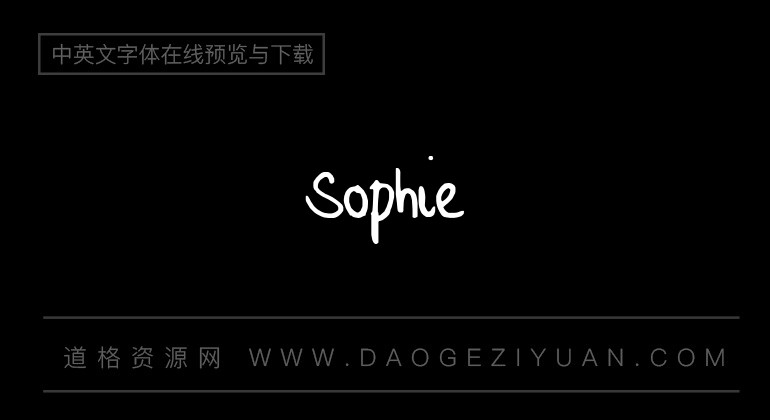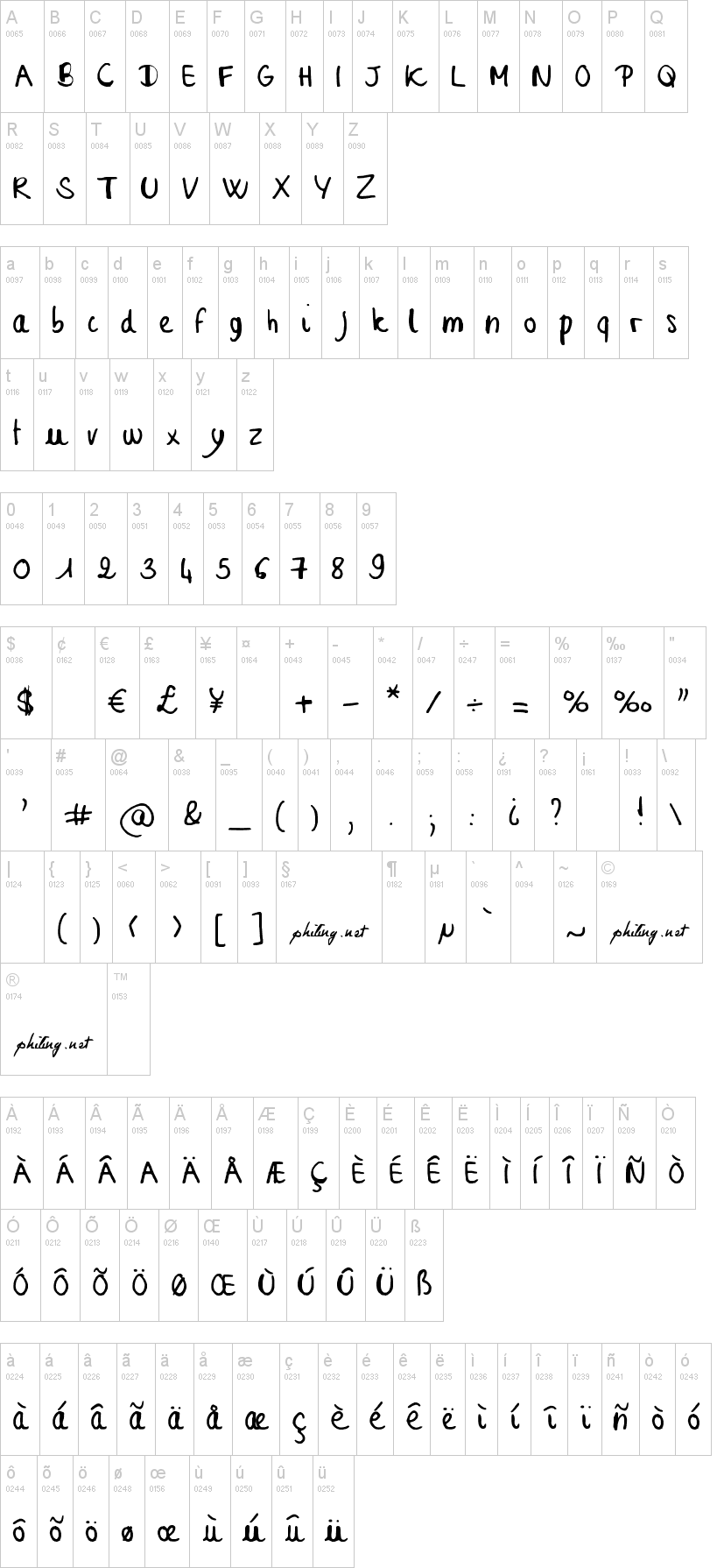
Sophie
Sophie字体是一款简洁、清新、优雅的英文字体,它是由英国设计师Sophie Smith设计的。Sophie字体具有优雅的曲线,清晰的细节和舒适的空间感,可以让文字显得更加精致大气。它的英文字母拥有细腻的曲线,清晰的细节,让文字充满动感。此外,Sophie字体还具有英文字母的自然变形,可以帮助设计师更好地表达自己的想法,创造出更加优雅的设计作品。
Sophie是一款非常不错的手写艺术字体,具有很好的视觉感,适合于文化类的宣传设计、商业类品牌的广告和产品包装设计以及个性化文字排版等较多场景。